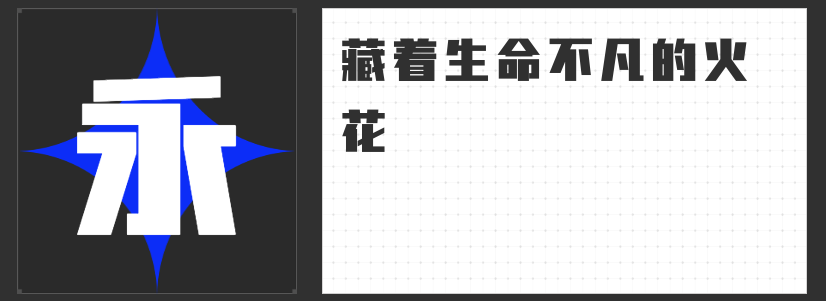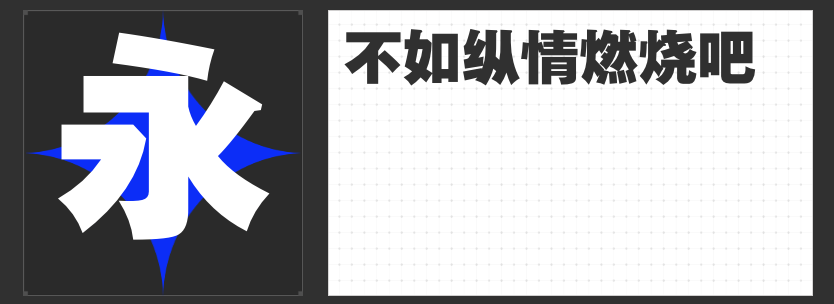
七夕设计字体精选:四款硬核黑体解锁浪漫商业视觉新表达
七夕作为兼具传统底蕴与现代浪漫的营销节点,设计需兼顾视觉冲击力与情感传达。本期推荐四款风格鲜明的黑体字库字体,以刚劲笔触演绎东方柔情,为节日海报、商品包装、线上宣传等场景注入高级感与记忆点。
一、励字开拓者简 特黑
这款字体以直线为语言,通过棱角分明的笔画构建出极具现代感的框架。方正字型与均匀布白传递稳定感,而镜像化处理的撇捺点画则暗藏巧思——如同银河两岸的星轨对称,呼应七夕“鹊桥相会”的平衡之美。去钩化设计简化视觉噪点,适合作为主标题承载品牌核心信息,在繁复的节日设计中以理性美学脱颖而出。
二、励字跨界黑简 超级黑
粗度夸张的直线奠定力量基调,微抬的曲线钩画则如流星划破夜空,为厚重字体注入灵动气息。90%字面率与宽大中宫确保远距离可读性,特别适合户外灯箱或电商首页大标题。当这款字体与织女星云、剪纸喜鹊等传统元素结合时,粗犷笔触能完美平衡图案的细腻感,形成刚柔对话的戏剧张力。
三、励字励黑简
无衬线装饰与正方形字面构建出如碑刻般的庄重感,超粗笔画如同用金石镌刻的誓言,与七夕“长久”的寓意形成隐喻呼应。方头起笔与无字肩折笔强化视觉穿透力,即使缩小用于商品标签或社交媒体配图,依然能保持清晰辨识度。这款字体适合传递品牌价值主张,让促销信息升华为文化宣言。
四、高手平方北半川劲黑体
竖粗横细的非常规比例打破黑体刻板印象,方正规整的字型中暗藏俏皮基因。当这款字体与卡通化牛郎织女IP、表情包式文案结合时,能碰撞出意想不到的年轻化火花。其趣味感并非削弱节日仪式感,而是以轻松姿态拉近与Z世代消费者的距离,适合社交媒体互动海报或限定款包装设计。
这四款字体如同四把视觉钥匙,助你在七夕营销中解锁传统与现代交融的独特美学语言。